圆润的字体是一种日常频繁使用的字体,中文圆体是由黑体字衍生而来的,大概出现于清朝末期,字体的拐角处、笔画末端都多为圆弧状。字体清晰、端正、朴实、易于 字体识别 ,没有太多华丽的装饰 。
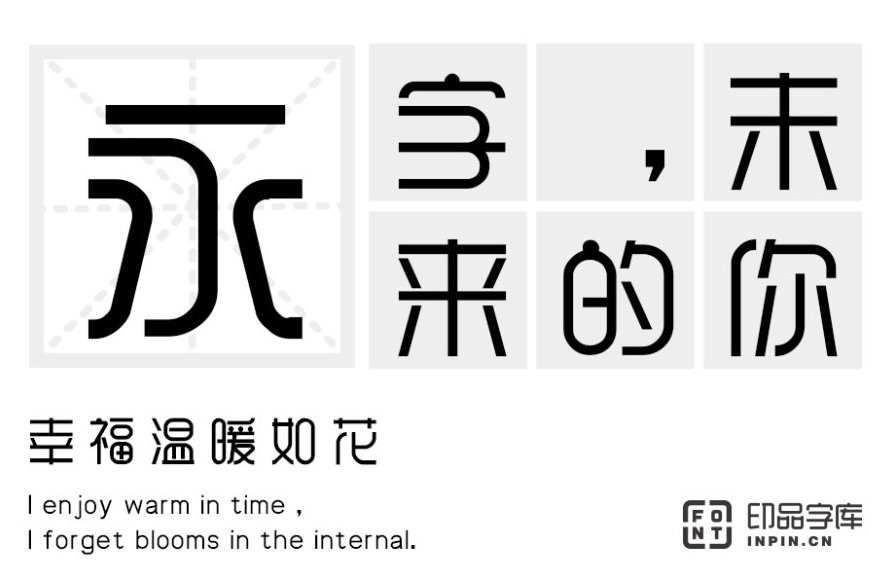
印品雅圆体:这款字体对弧形做了内凹外凸的处理,使得笔画更加居中圆滑。表面结构匀称统一,字形多了细致比例的调整,整体视觉感受更加珠圆玉润。在加强了装饰感的同时增添了一丝俏皮可爱。适用于游戏、logo、广告、印刷、屏幕显示、影视、印章等多种领域。
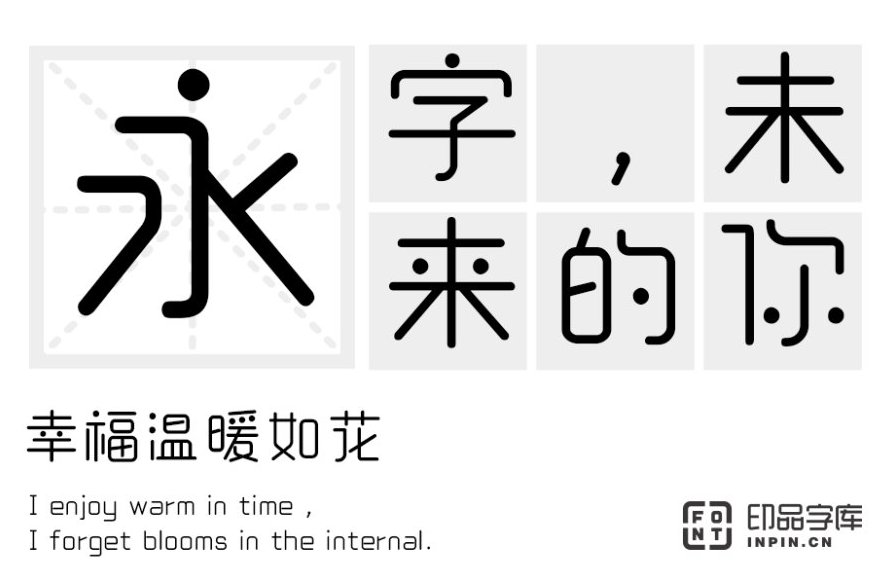
印品睿圆体:这款字体保留了圆体的特点,在笔画的走向、粗细变化上做了细致的处理,再在字重加入圆点设计,使字体看上去更加鲜活、灵动,视觉上更加有时尚感。适用于logo、广告、印刷、屏幕显示、影视等多种领域。
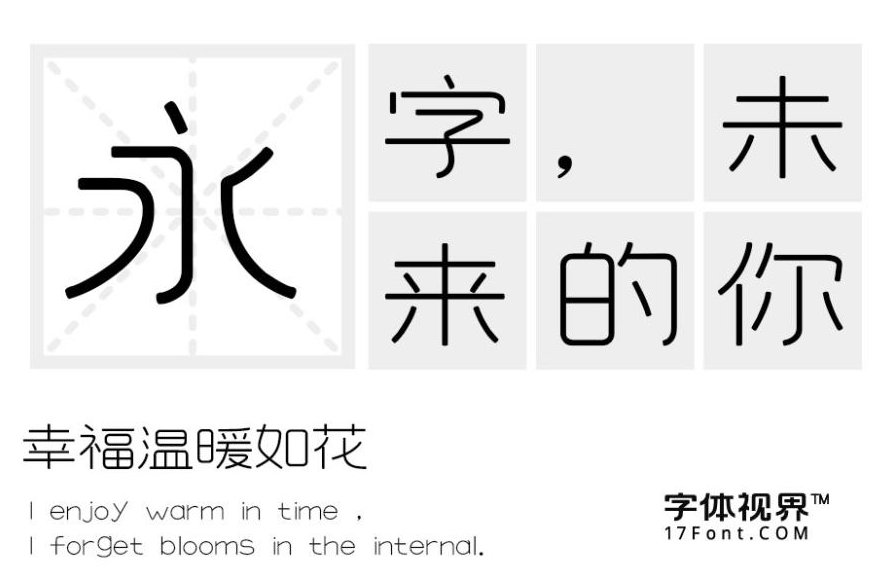
上首秀圆体:这款字体风格清新秀丽,比起传统圆体笔画较于瘦长,转角处却保留了圆润感,柔和却现代感十足。适用于logo设计、广告标语、商业广告等高端属性。
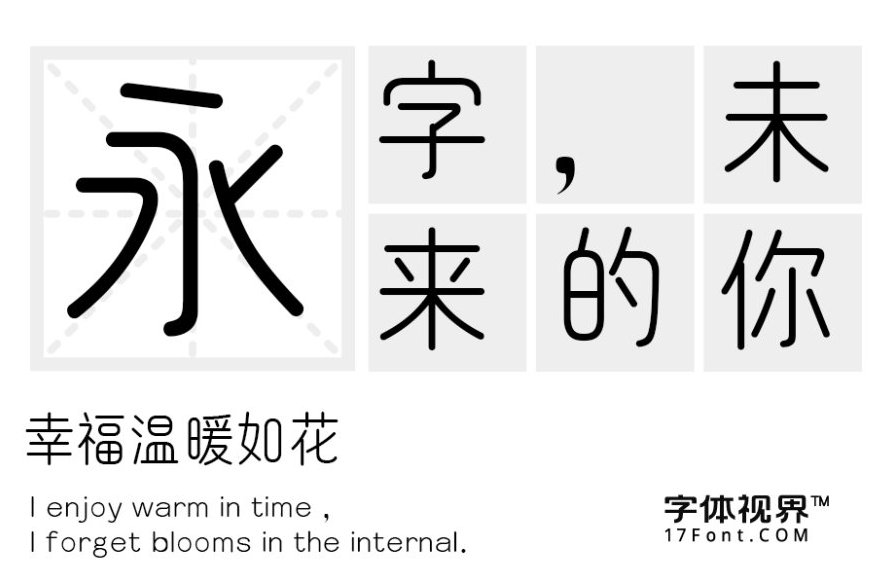
三极古圆简体:这款字体大面积保留了传统圆体的朴拙感,字形融合了象形、篆书等古朴字形,粗细匀称,转折圆润饱满。字形清晰易识别,在搜字体网上看图找字 方便,视觉效果简洁轻巧。实用性强,适用于正文及标题、logo设计、印刷、屏幕显示、影视等领域。